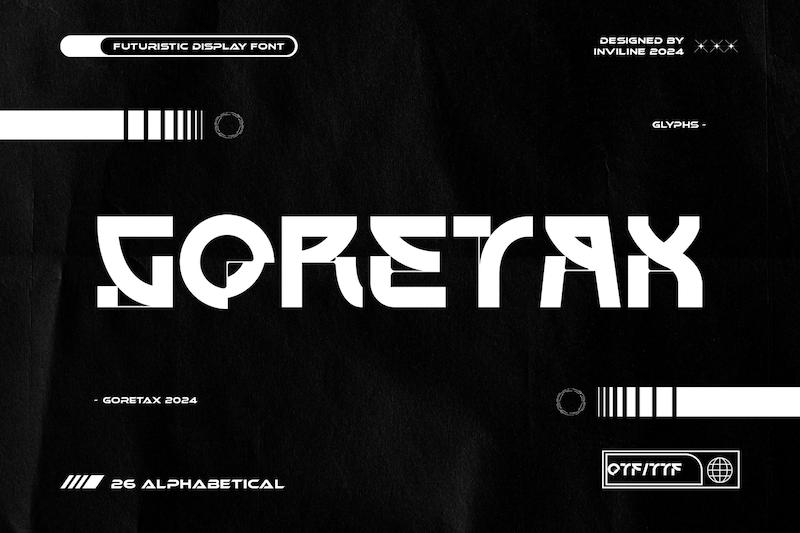
گورتکس، یک فونت دیسپلی بولد و فیوچرستیک است که برای جلب توجه ساخته شده است. با برشهای هندسی تیز، اشکال بریدهشده و منحنیهای رباتیک، برای جلوههای بصری پیشرو در حوزه فناوری، از رابطهای کاربری علمیتخیلی گرفته تا هویتهای بصری بازیها، مناسب است. ساختار گلیف (حروف) تجربی و کنتراست قوی آن، تعادلی محکم بین ساختار و انتزاع ایجاد میکند؛ که آن را برای عناوین برجسته، پوسترها، لوگوتایپها و موشن گرافیکها ایدهآل میسازد.
حروف بزرگ و کوچک
اعداد و علائم نگارشی
سمبلها و آلترنیتهای سبکی (برای گلیفهای منتخب)
طراحی شده برای استفاده چاپی و دیجیتال
برندینگ موسیقی تکنو / الکترونیک
پوسترهای سایبرپانک و علمیتخیلی
بستهبندی محصولات آیندهنگر
لوگوهای ورزشهای الکترونیک (اسپرت) یا بازیها
تصاویر بصری رابط کاربری (UI/UX)
موشن گرافیکهای تجربی
تامنیل و عناوین آغازین یوتیوب
اسلایدها و تصاویر کلیدی ارائهها